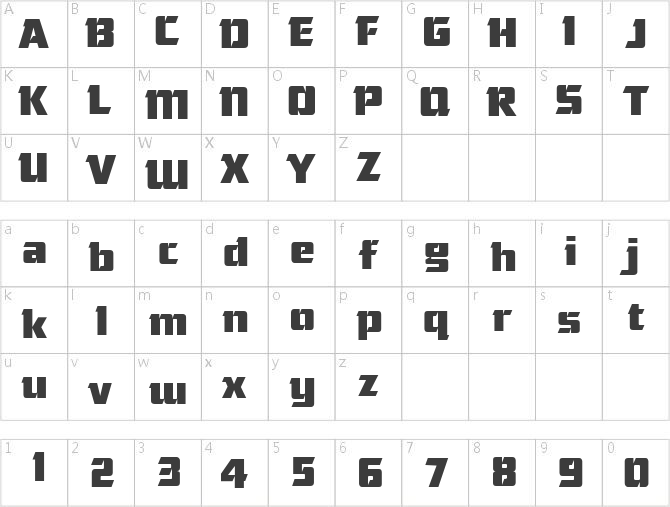
Ultra Serif SF 詳情頁(yè)
Ultra Serif SF字體字庫(kù)是一款讓人賞心悅目、百看不厭的英文字體,適合各類廣告和產(chǎn)品包裝設(shè)計(jì)應(yīng)用,字體大小0.03MB,格式為ttf字體,上傳用戶是眾聯(lián)齊成,作者/版權(quán)方為未知